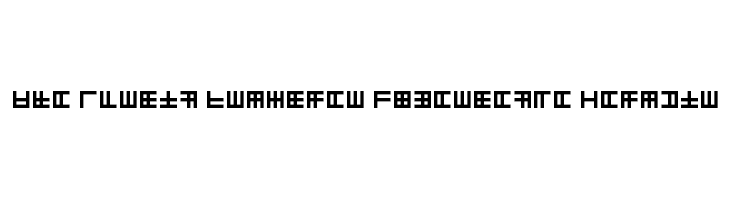
A futuristic, angular font with sharp edges and geometric shapes.
A bold, modern font with a unique gradient line effect for a dynamic look.
A graceful, cursive font with elongated, flowing letterforms.
A graceful and elegant handwritten cursive font with flowing letterforms.
A futuristic, angular, and italicized font with a robotic feel.
A whimsical, star-studded decorative font perfect for festive occasions.
A bold, angular outline font with a modern, edgy design.
A playful, hand-drawn font with tall, narrow letters and quirky details.
A bold, geometric font with a modern, digital aesthetic.
An ornate blackletter font with high contrast and gothic flourishes.
A playful, brush-style font with a watercolor effect.
A modern, angular font with a futuristic and geometric design.
A futuristic, italicized font with sharp, angular lines and a dynamic style.
A bold, handwritten script font with a playful and energetic style.
A bold, graffiti-style font with shadowed, jagged letters.
A bold, hand-drawn font with an irregular and quirky style.
A refined serif font with a semi-condensed, thin structure, ideal for elegant and professional use.
A modern, elegant font with angular uppercase and cursive lowercase letters.
A decorative font with horse silhouettes integrated into each letter.
A bold, geometric font with a modern, angular style.
A pictorial decorative font featuring stylized female portraits.
A playful, heart-themed decorative font with whimsical elements.
A bold, graffiti-inspired font with dynamic, hand-drawn characters.
A bold, three-dimensional font with a vintage, decorative style.
A playful and quirky font with unique, irregular letterforms.
A playful, handwritten font with consistent strokes and rounded edges.
A playful, modern font with circular decorative elements.
A bold, geometric font with angular lines and a strong, modern presence.
A dynamic and flowing script font with elegant cursive letterforms.
A bold, distressed font with a grunge aesthetic and rugged appearance.
A modern, geometric sans-serif font with a clean and minimalistic design.
A bold, geometric font with a futuristic and industrial design.
A sophisticated cursive script with elegant, flowing strokes and ornate flourishes.